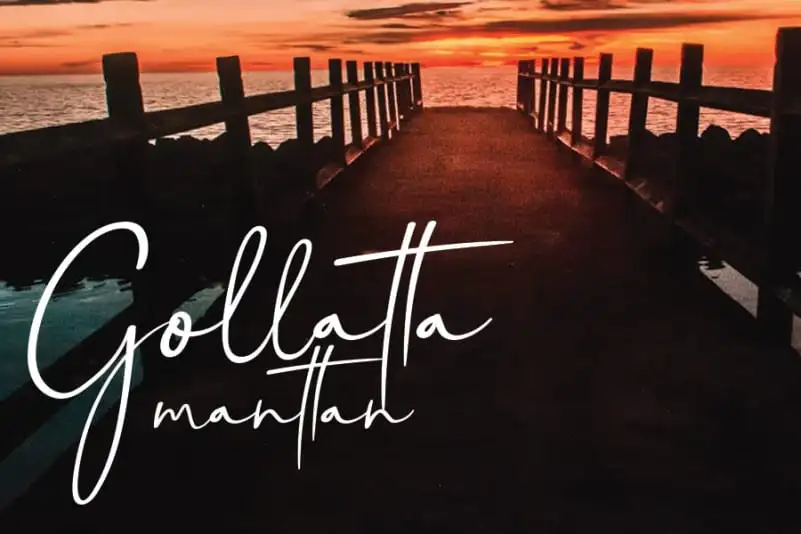
Gollatta manttan Handwritten Font – Download Grátis
A fonte ‘Gollatta manttan Handwritten Font’ é uma escolha perfeita para quem busca uma escrita fluente e encantadora. Embora não seja exatamente um livro de estilo, essa elegante fonte pode transformar qualquer projeto design em algo único e imersivo. Suas linhas suaves e agradáveis são perfeitas para aumentar o nível de complexidade e beleza em designs que vão desde logotipos e rótulos até assinaturas personalizadas e invitations de casamento. Sua versatilidade permite que ela se encaixe facilmente num vasto espectro de projetos, incluindo criações para marcas, headlines, design de casamentos, convites, assinaturas e muito mais. Este é um recurso gráfico único e sofisticado, certo de aprimorar qualquer projeto à qual seja aplicada. Experimente ‘Gollatta manttan Handwritten Font’ e observe como ele pode transformar sua próxima criação design em algo realmente especial.